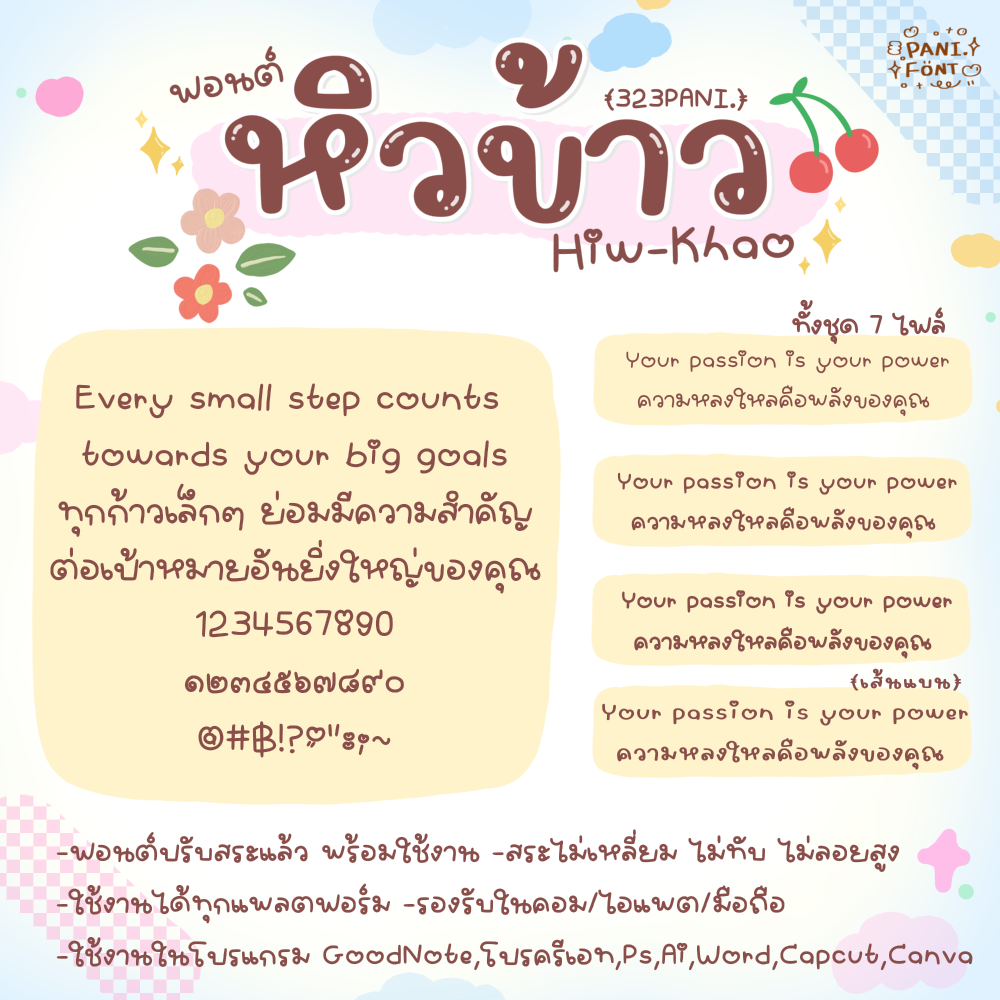
323PANIHiwKhao
ชุดนี้ตั้งใจเขียนแนวบาง ตัวชิดหน่อย ให้อารมณ์เขียนเอง เขียนสด ตัวอักษรจะดุ๊กดิ๊กนิดๆ
(แอนทำไฟล์หนา กับเส้นแบน และชุดช่องไฟกว้างเพิ่มให้ด้วยค่ะ)
ชุดนี้จะแต่งภาพง่าย ทำคลิปน่ารัก ไม่จำเจ
แต่ยังคง อ่านง่าย สบายตา สไตล์แอนค่ะ????